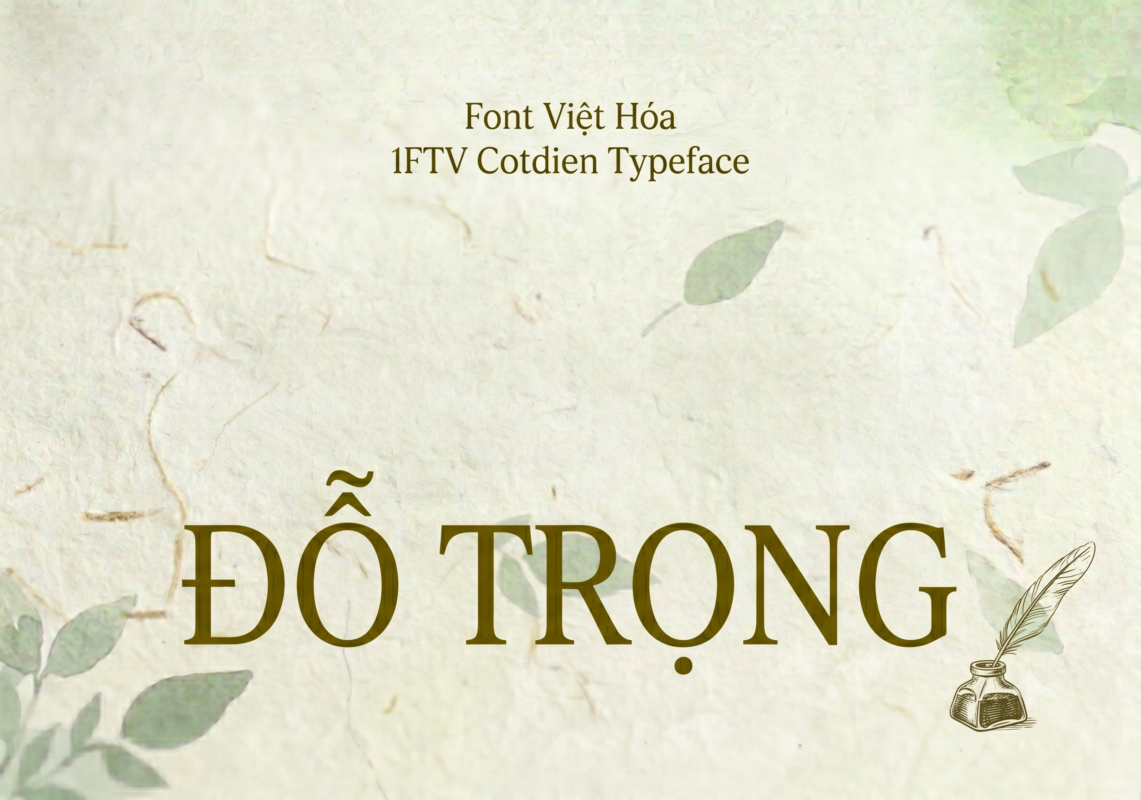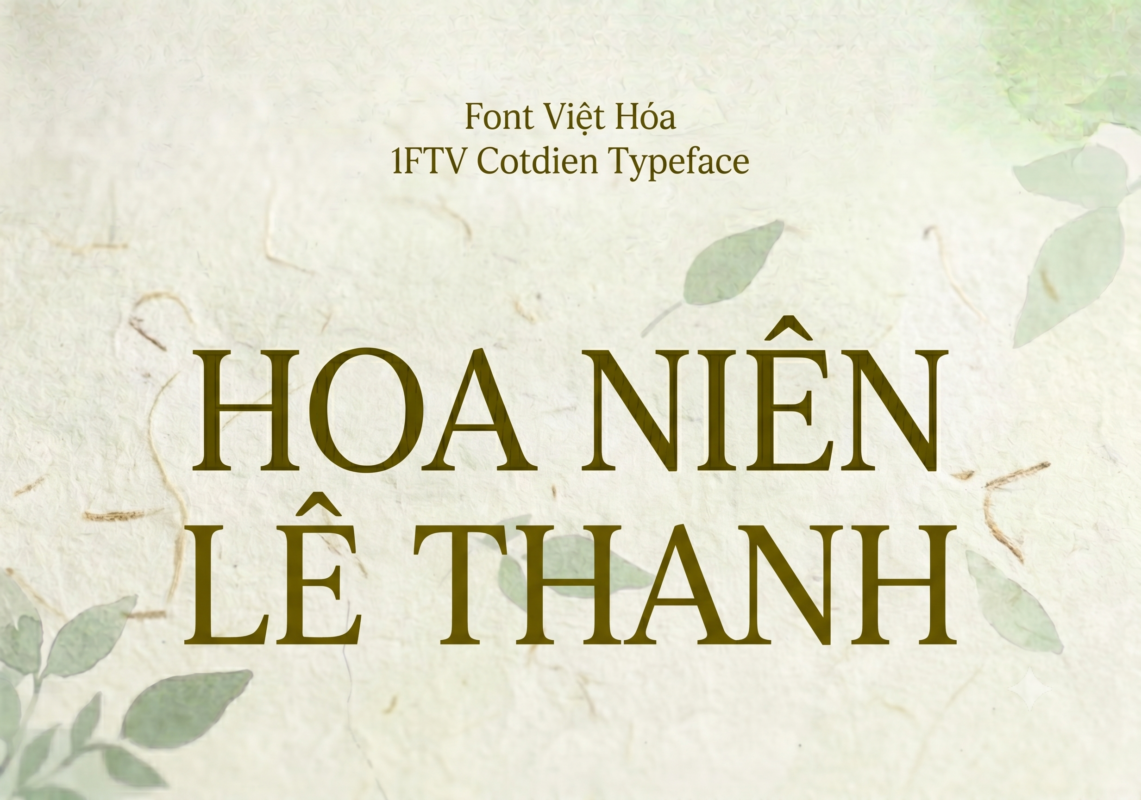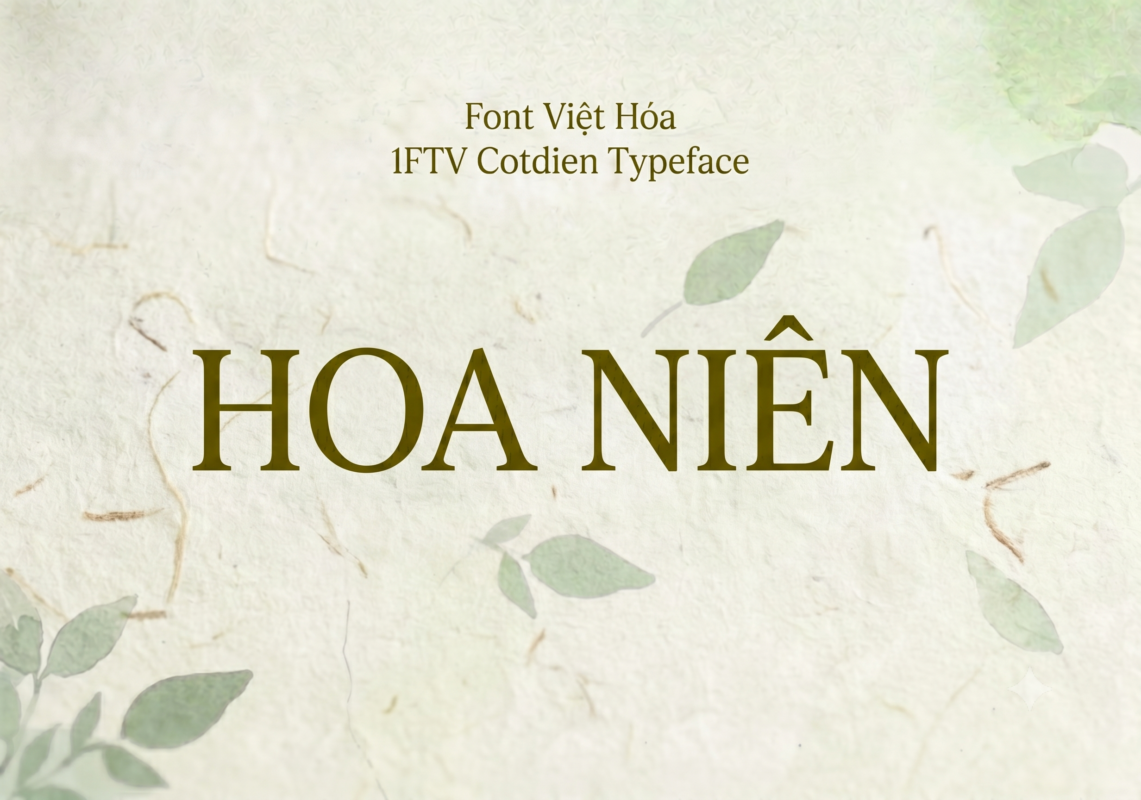
1FTV Cotdien Typeface
1FTV Cotdien Typeface là một phông chữ thuộc thể loại display (hiển thị) mang đậm tinh thần cổ điển và nghệ thuật hình khối geometric. Định dạng chữ được tối ưu hóa theo phom dáng cao, hẹp (condensed), tạo nên một cấu trúc thanh thoát nhưng không kém phần vững chãi, độc lập.
Giới thiệu về Font 1FTV Cotdien Typeface
Đặc điểm nổi bật của phong cách thiết kế Cotdien Typeface
Sức hút khác biệt của 1FTV Cotdien Typeface đến từ những đường cắt góc vuông vắn và phom chữ thuôn dài độc đáo. Các ký tự như O, D, S, B không bo tròn theo cách truyền thống mà được hình khối hóa bằng những đường thẳng và góc cạnh dứt khoát, mô phỏng lại phong cách vẽ chữ trên các biển hiệu quảng cáo vẽ tay ở Việt Nam những thập niên trước.
Phông chữ được thiết kế theo dạng All-Caps (viết hoa toàn bộ các ký tự chữ cái), giúp tạo ra sự đồng bộ tuyệt đối về mặt chiều cao và bố cục khi sắp xếp các dòng chữ cạnh nhau. Nhờ khoảng cách giữa các nét được tính toán kỹ lưỡng, kiểu chữ này mang lại một cảm giác vừa tối giản, vừa nghệ thuật, rất phù hợp cho các thương hiệu thời trang vintage, quán cà phê cổ điển, hay các ấn phẩm văn hóa nghệ thuật.
Hệ thống khoảng cách giữa các chữ (kerning) và độ giãn dòng (tracking) được căn chỉnh chuẩn xác, tránh hoàn toàn hiện tượng các chữ cái bị dính vào nhau gây khó đọc. Bên cạnh bộ chữ cái All-Caps đồng đều, bộ phông còn tích hợp đầy đủ dãy số từ 0-9 cùng hệ thống các ký tự đặc biệt, dấu câu căn bản (.,;:''"(!?)+-*/=), giúp người dùng dễ dàng biến hóa nội dung mà không gặp bất kỳ lỗi định dạng hay thiếu ký tự nào.
Hình ảnh Demo thực tế của Font 1FTV Cotdien Typeface
Để giúp bạn dễ dàng hình dung độ sắc nét và tính tương thích của phông chữ này trên các kích thước hiển thị khác nhau, hãy xem qua bảng mô phỏng từ size nhỏ đến lớn:
Kích thước nhỏ (12pt – 24pt): Các đường nét thanh mảnh vẫn hiển thị rõ ràng, form chữ đứng giúp tiết kiệm diện tích chiều ngang một cách tối đa.
Kích thước lớn (36pt – 72pt): Các góc cạnh hình khối và cấu trúc hình học của chữ hiện lên cực kỳ rõ nét, tạo hiệu ứng thị giác mạnh mẽ, thích hợp làm tâm điểm cho mọi ánh nhìn.
Ứng dụng của Font Cotdien Typeface trong thiết kế đồ họa và làm video
Nhờ sở hữu nét cá tính độc nhất, 1FTV Cotdien Typeface mở ra không gian sáng tạo rộng mở cho các dự án truyền thông và marketing:
Thiết kế Poster, Banner Concept Cổ Điển: Rất thích hợp làm tựa đề cho các poster phim, ảnh quảng bá sự kiện âm nhạc indie, hoặc banner cho các chiến dịch mang hơi hướng hoài niệm, hoài cổ.
Tạo Text Điểm Nhấn Trên Video Ngắn: Định dạng chữ All-Caps cao ráo này làm các cụm từ key-word, tiêu đề mở đầu video trên TikTok, Reels hay Shorts trở nên cực kỳ nghệ thuật và thu hút người xem lướt chậm lại.
Nhận Diện Thương Hiệu Cửa Hàng Vintage: Đây là lựa chọn tuyệt vời để thiết kế logo dạng chữ, menu nhà hàng, biển hiệu cho các quán cà phê, tiệm quần áo đi theo phong cách xưa cũ, mộc mạc.
Thiết Kế Sách, Tạp Chí Nghệ Thuật: Phù hợp làm chữ tiêu đề chương, bìa sách hoặc các trang layout tạp chí thời trang đòi hỏi gu thẩm mỹ cao và sự khác biệt.